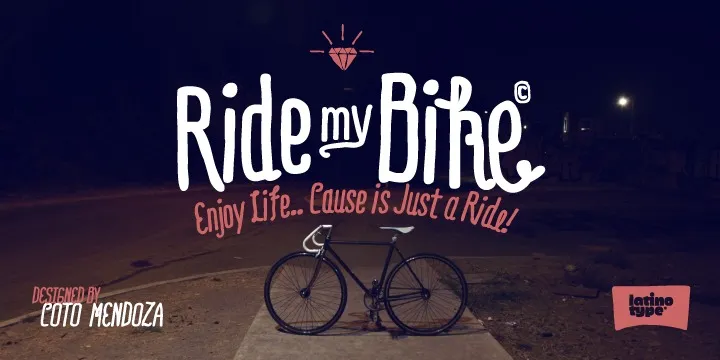
Ride my Bike Font Family – Download Grátis
A Ride my Bike Font Family é uma proposta fresca e natural para entusiasmados amantes do desenho tipográfico, inspirada no estilo urbano e na cultura que se move pedalando por nossas cidades. Inspirado nas cores vibrantes das calçadas de São Paulo ou a cidade mais vibrante da América Latina, essa fonte é uma elegância minimalista ideal para criações playfully urban. Essa família de caracteres foi criada pelo designer Hamilton, e oferece um equilíbrio entre os detalhes meticulosamente cuidados e a facilidade de uso intuitiva, tornando-a perfeita para designers amantes do estilo urbano que querem dar uma cara única e fresca às suas criações. Seja você um artista grafiti ou um designer gráfico, a Ride my Bike Font Family certamente fará seu estilo se destacar na multidão.